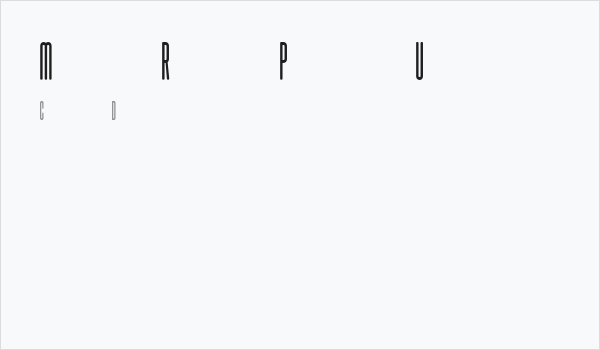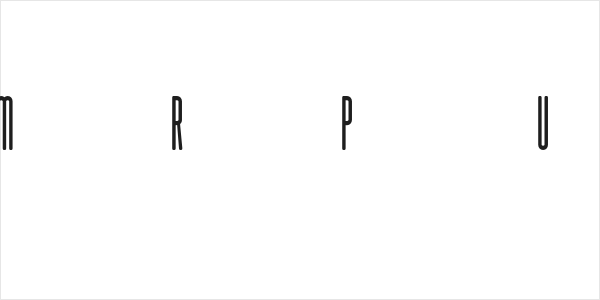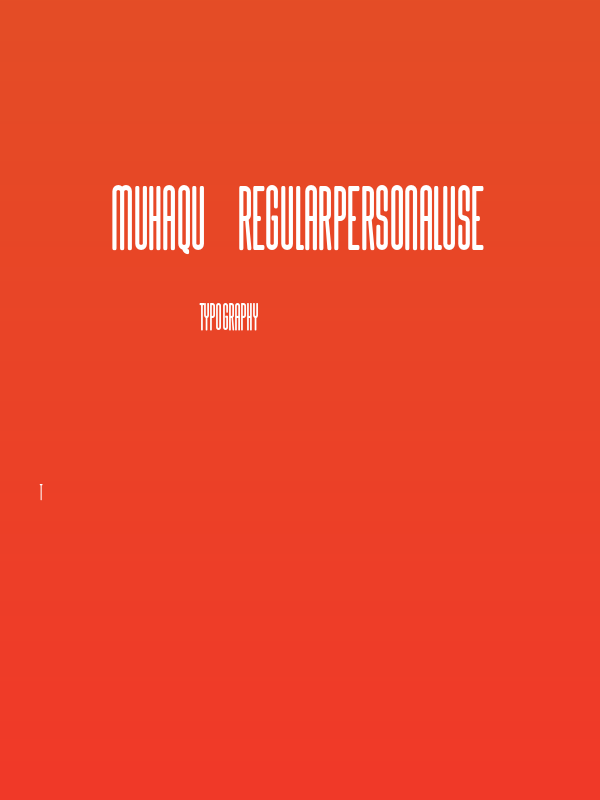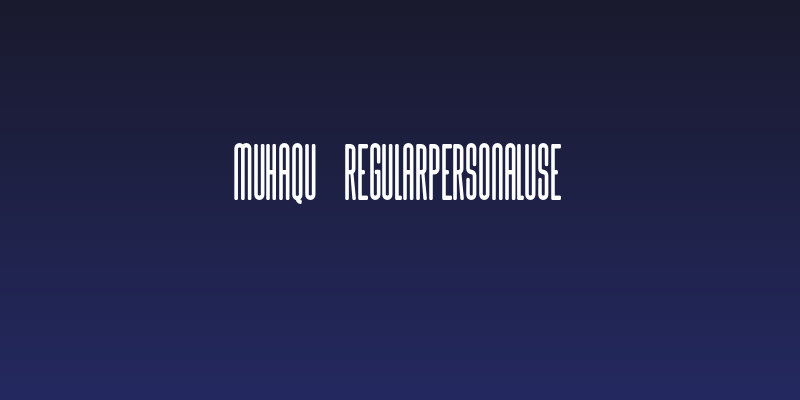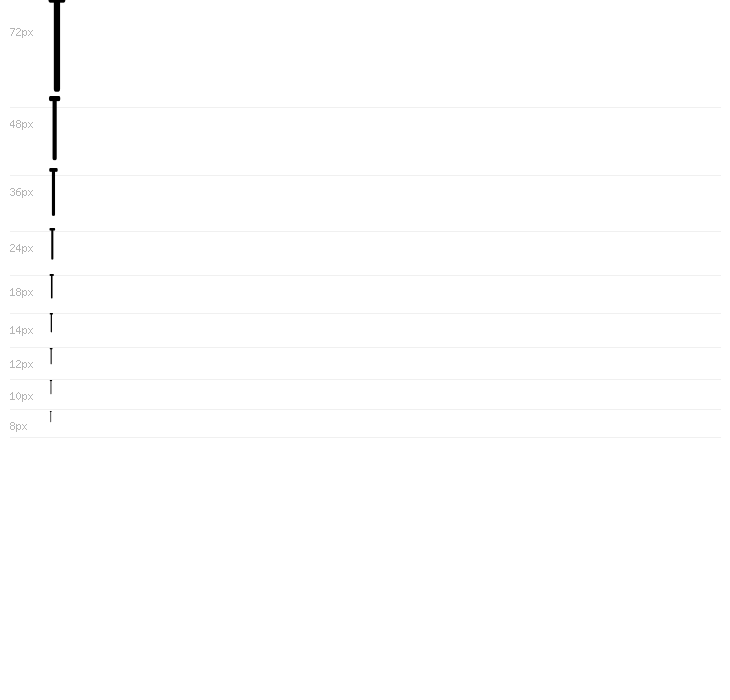
Muhaqu-RegularPersonalUse Font
✎ Modern
| Progetti proposti | Ideal for posters, headlines, and branding projects where a bold and modern statement is desired. |